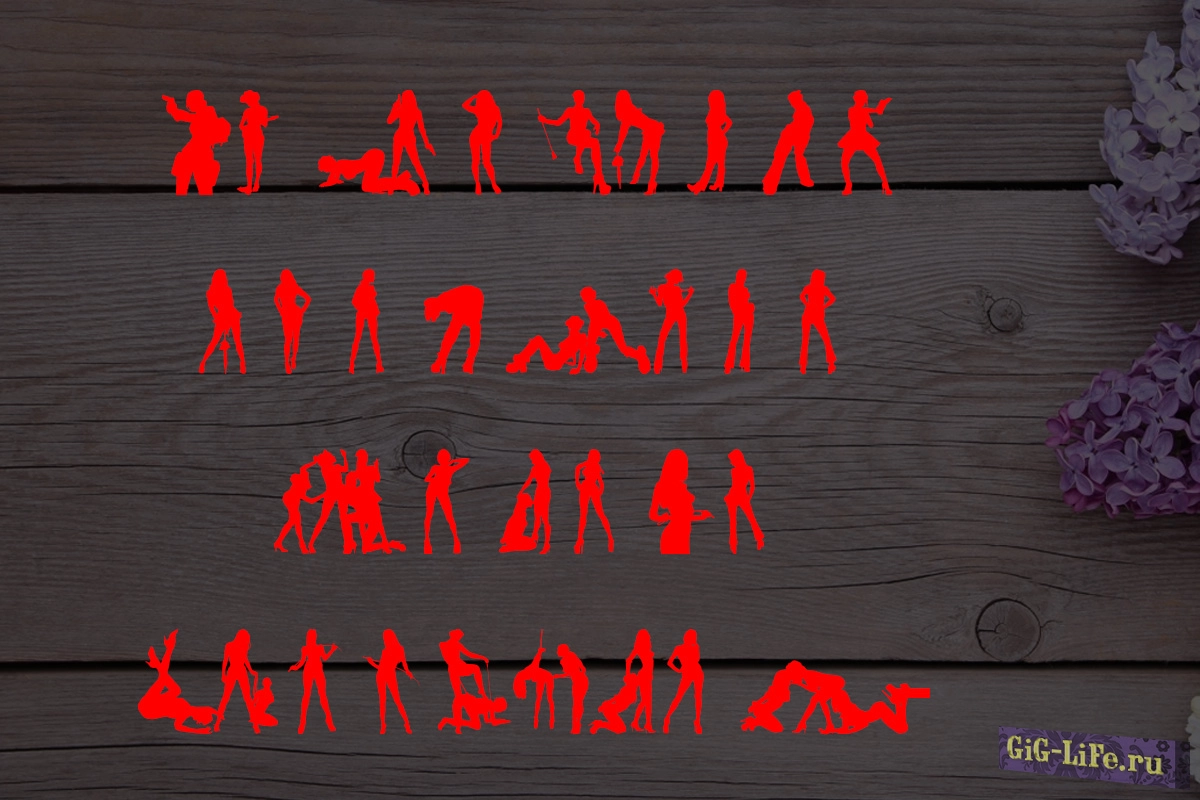
SexyDynamite - это эстетически привлекательный шрифт, специально созданный для применения в графическом редакторе Photoshop и других творческих проектах, исходя из символов.